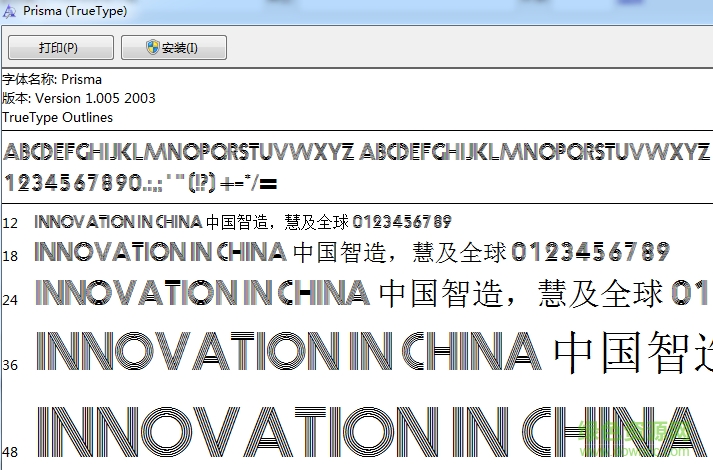
Prisma字體是一款超好用的英文字體,字體擁有十分完善的字庫(kù),這款字體看似由一條條線段組合而成,極具個(gè)性,有喜歡這款字體的朋友就趕快來(lái)綠色資源網(wǎng)下載使用吧!
Prisma字體是一款英文字體,該字體獨(dú)有的線條,讓用戶能夠輕松記住它,有需要的朋友就趕快來(lái)綠色資源網(wǎng)下載吧!